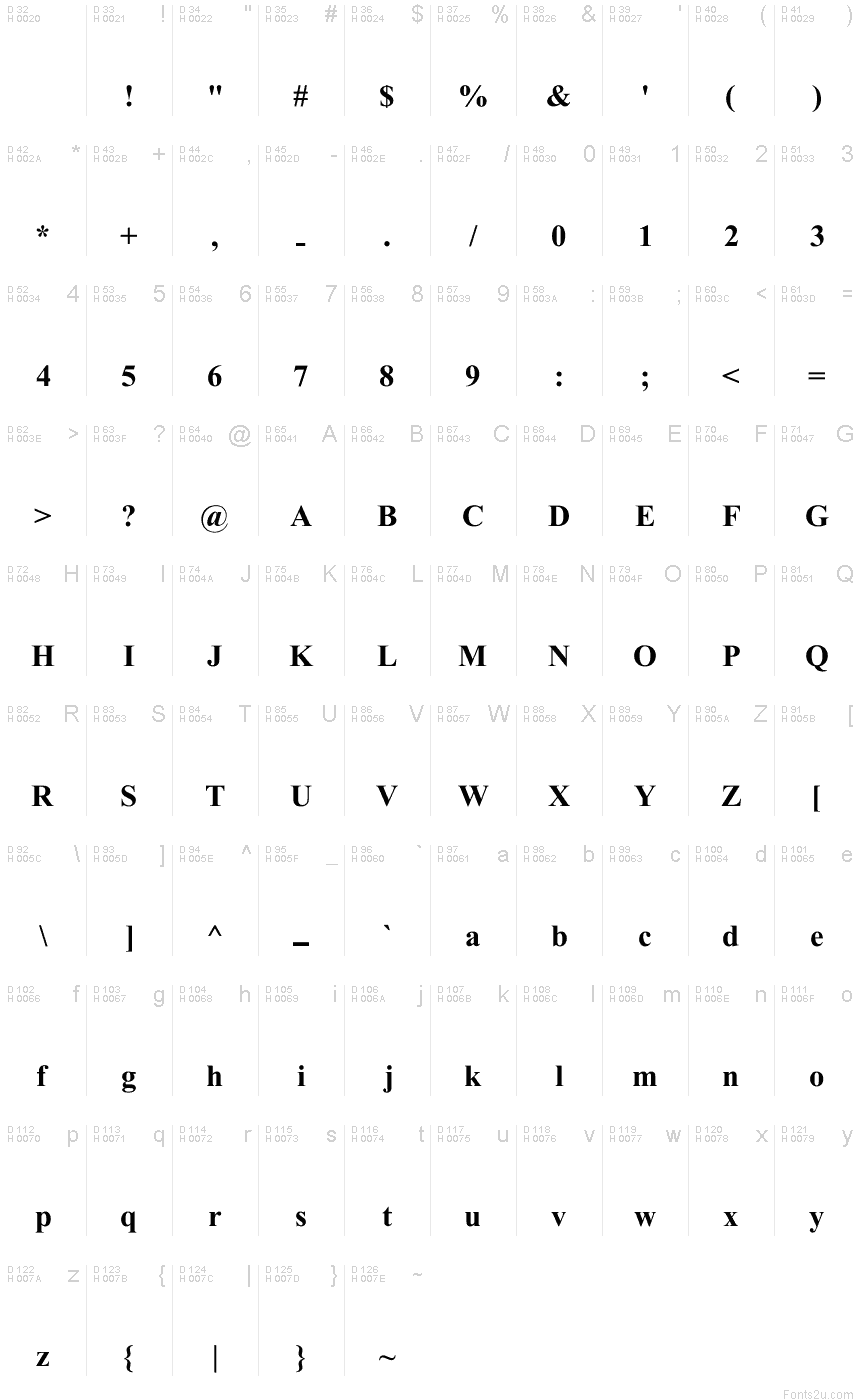
UKIJ Tuz Basma Bold, da Uyghur Computer Science Association, é uma fonte serifada gratuita com um toque de tipos de madeira. As letras parecem amplas e teatrais, misturando um peso vertical espesso com serifas rombas e algumas junções afiadas que conferem à fonte um ritmo de cartaz, em vez de um aspecto editorial.
Isso a torna uma escolha natural para cabeçalhos, cartazes de eventos culturais, capas de discos, cartões de título e manchetes curtas em embalagens, onde é necessária uma fonte gratuita com um tom histórico de impressão. Também funciona bem para monogramas e capitulares, já que as maiúsculas carregam massa e contraste suficientes para sustentar uma página ou capa sozinhas.